「絶対必須!色褪せない贅沢英語フォント大全集」の気になる中身をご紹介
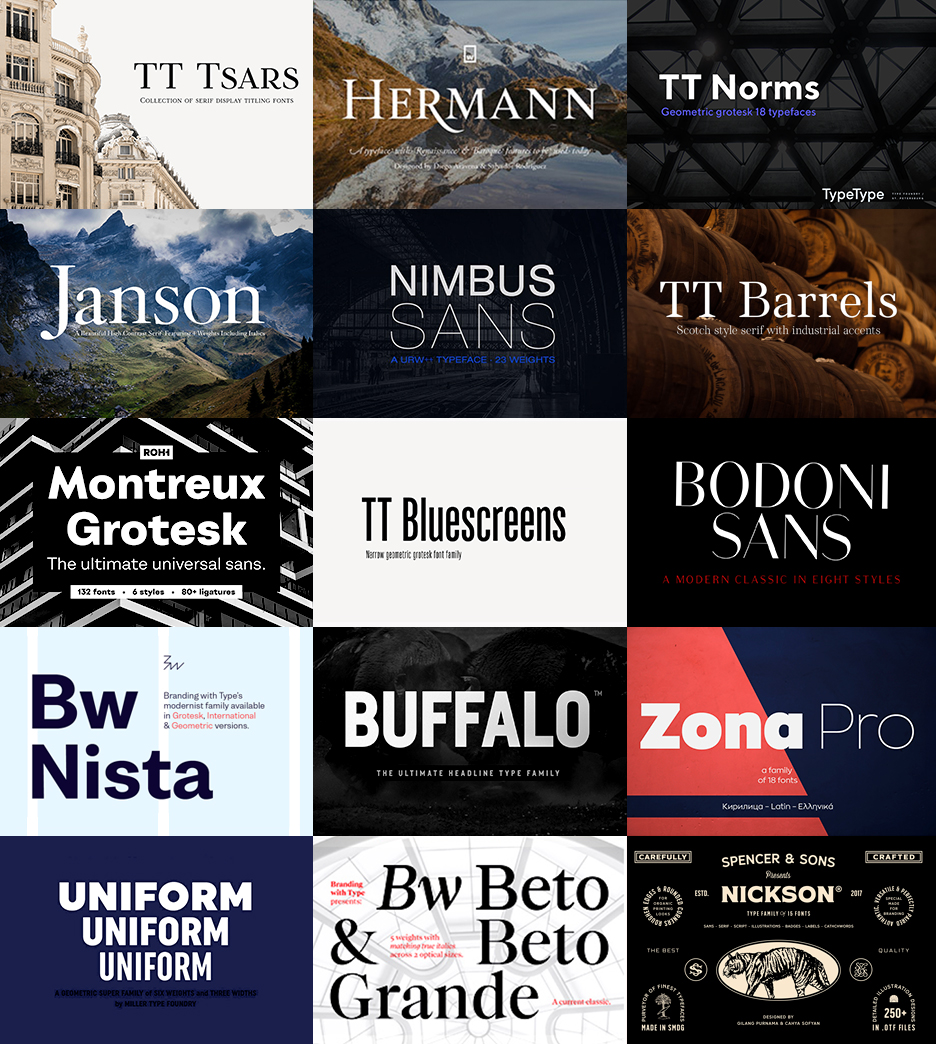
20書体を収録した美しいセリフフォント:TT TSARS
美しい20書体を揃えたセリフフォントコレクション「TT TSARS」。ユニークなリガチャ(合字)のデザインにも注目!ロゴデザインやブランディングに活躍するフォントです。
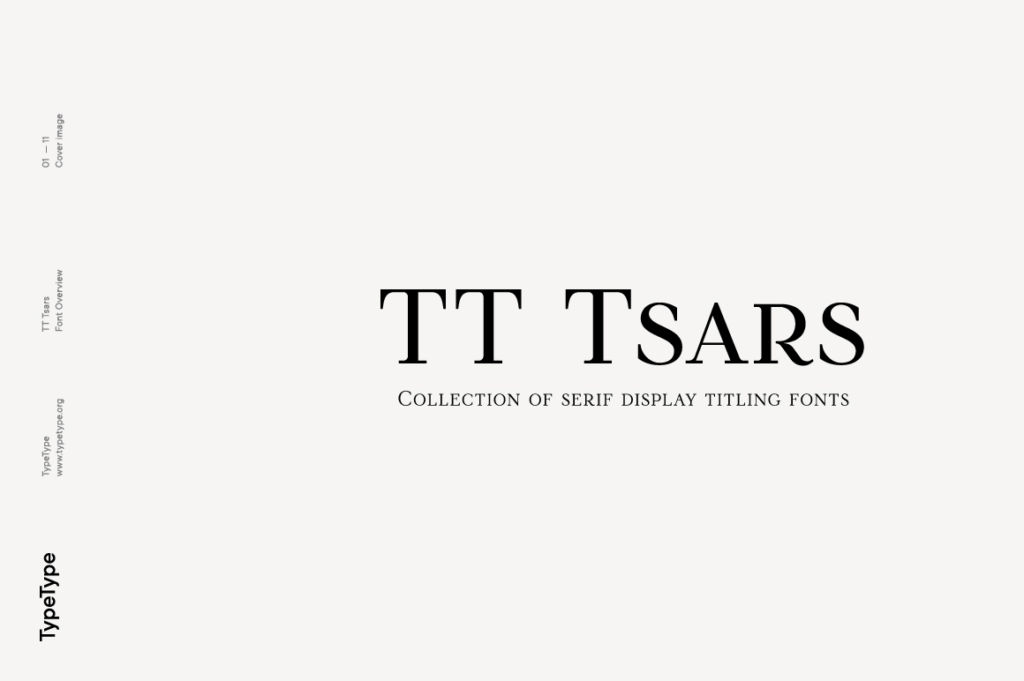
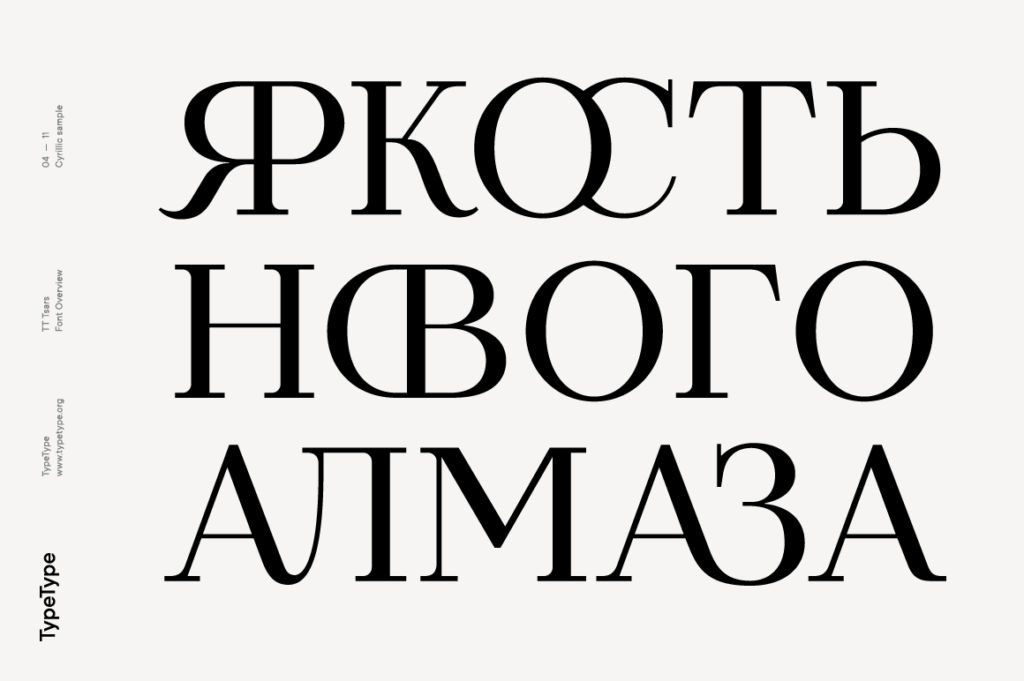
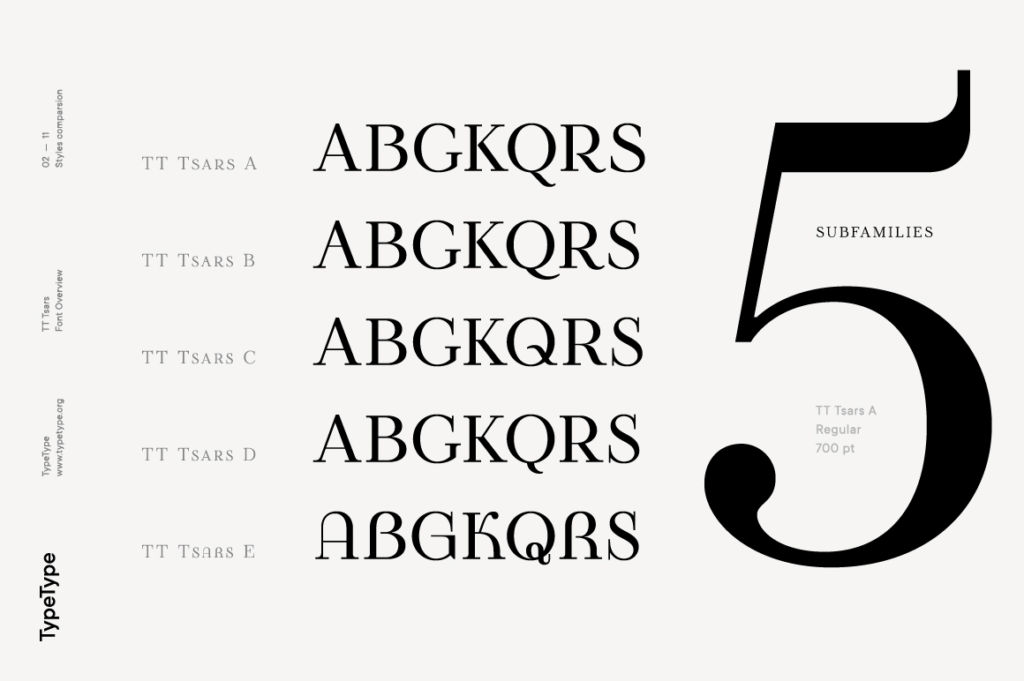
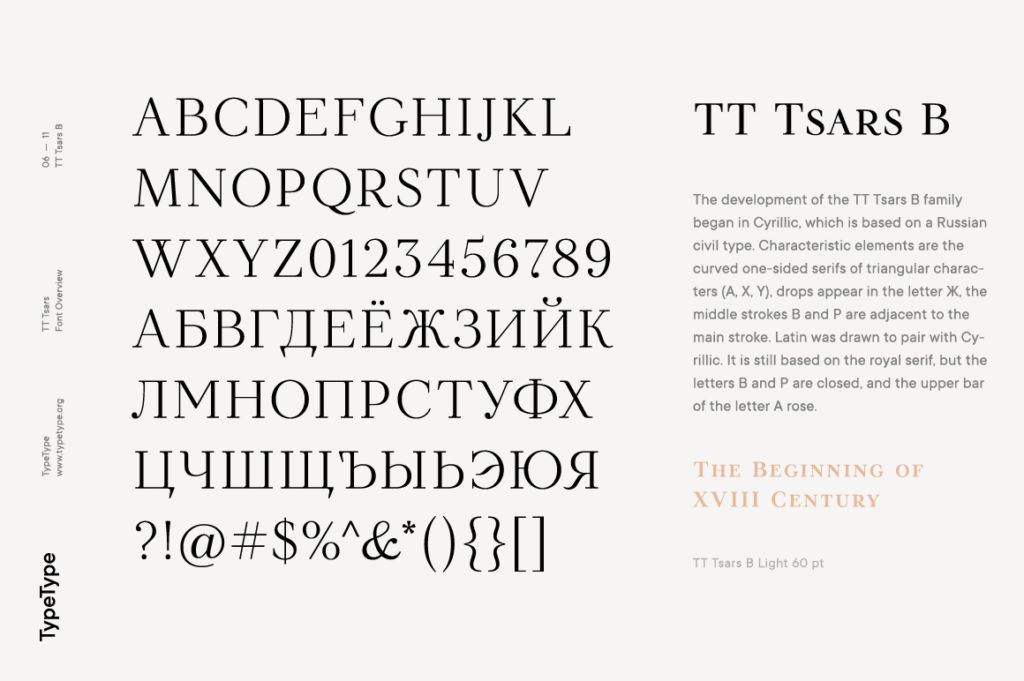
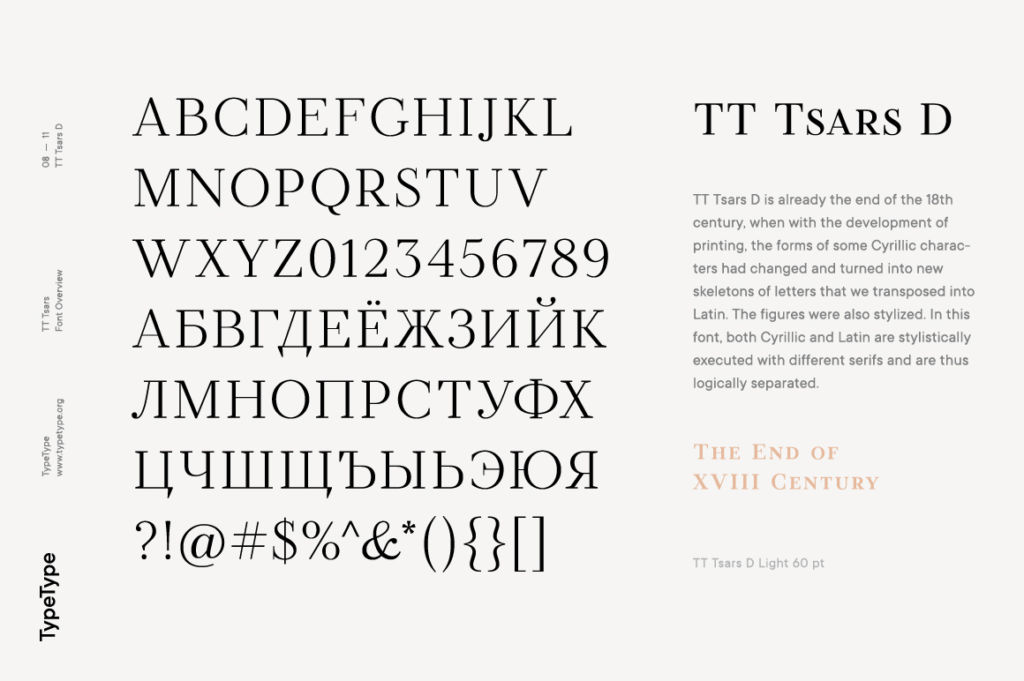
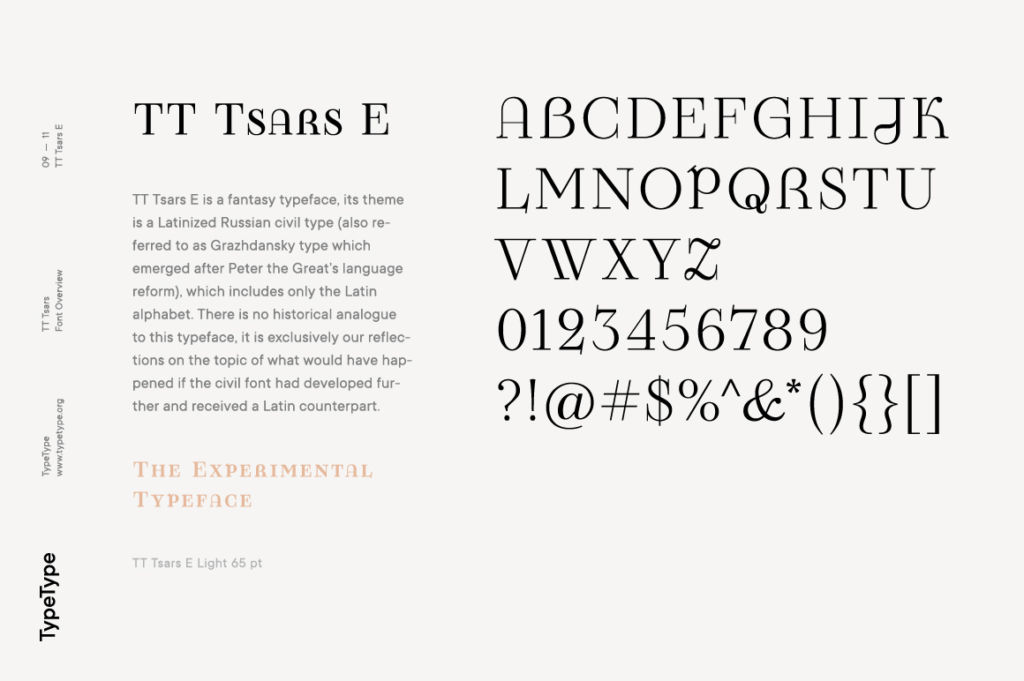
凝ったリガチャが楽しめるセリフフォント:TT BARRELS
18書体を収録したTypeTypeの「TT BARRELS」。ウェイトもライトからブラックまで用意されており、デザイン性の高いリガチャ(合字)も多数収録。一見かなり凝ったタイポグラフィも簡単にできますよ。
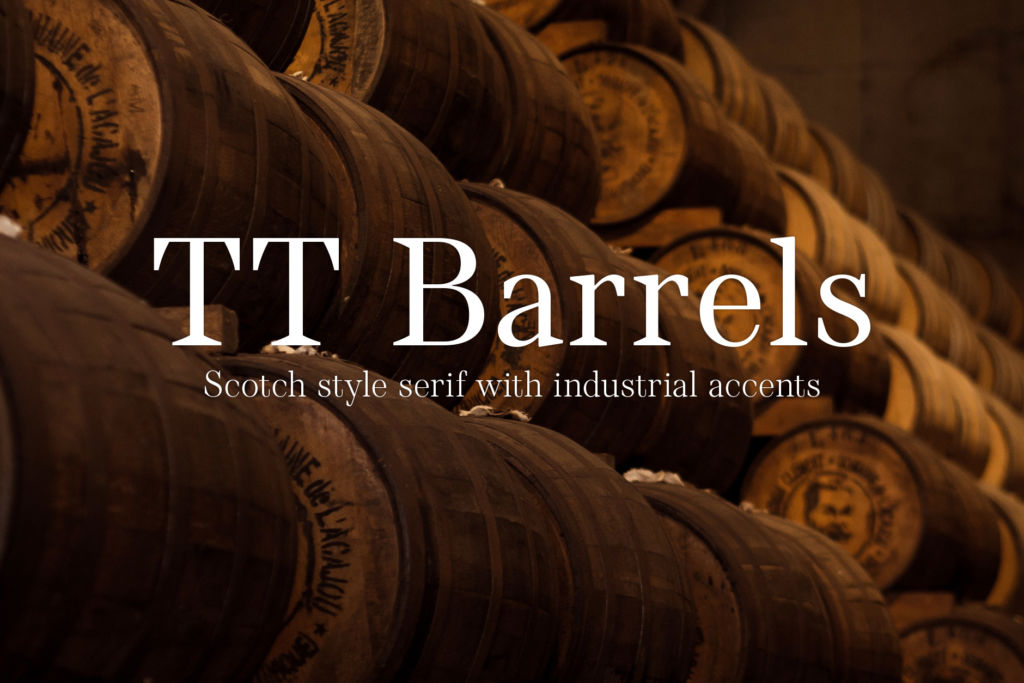
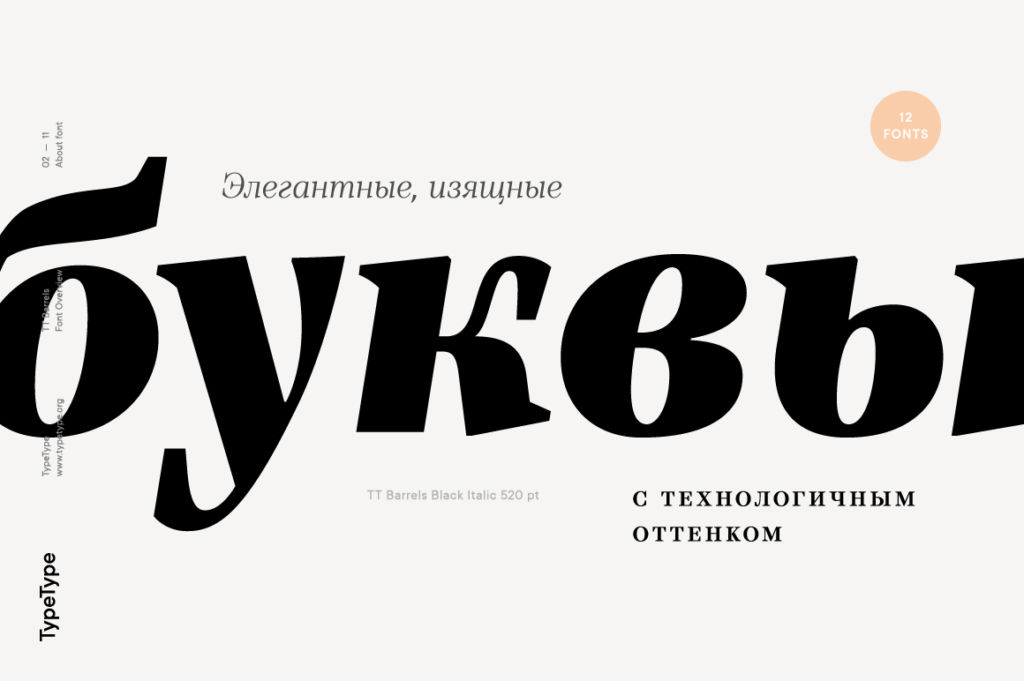
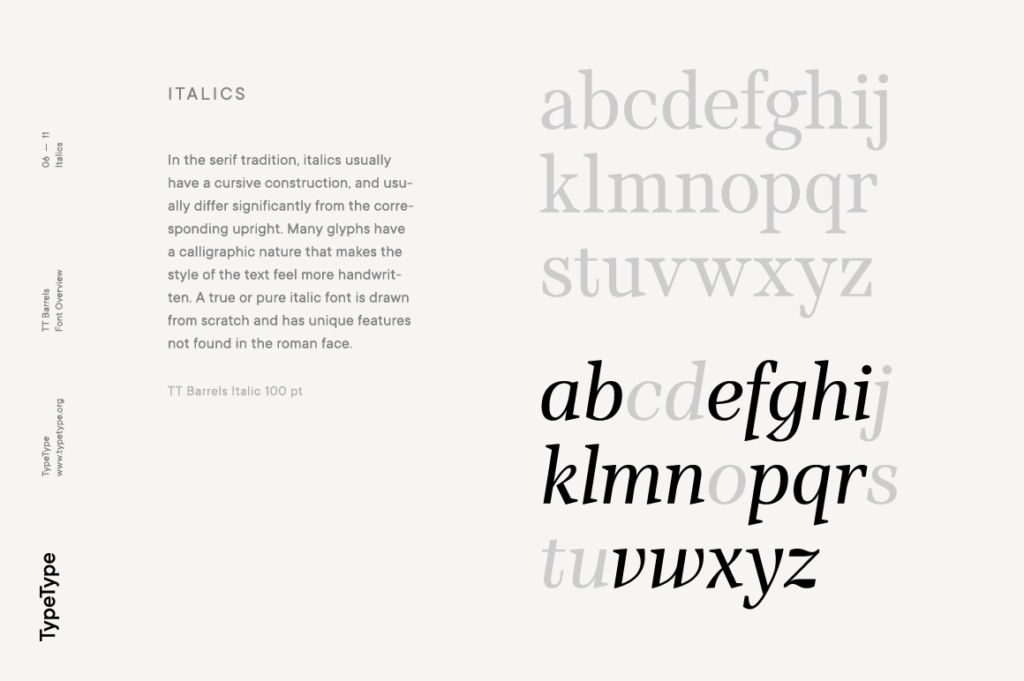
デザイン性の高い優雅なスウォッシュが魅力:HERMANN TYPEFACE
優雅なスウォッシュが魅力のセリフフォント「HERMANN TYPEFACE」。書籍の装丁やラベルのデザインをグッと格調高くしてくれます。
ウェイトのメリハリがポイント!BODONI SANS
縦ラインの太さが特徴の「BODONI SANS」。セリフフォントBODONIを連想させるクラシック感を残しつつ、現代風にアレンジされています。小さくても読みやすい文字で、様々な媒体に利用できますよ。
イラストやフレームを豊富に収録:S&S NICKSON FONT FAMILY
15種類のフォントはもちろん、イラストやフレームなど、ロゴやラベル作りに役立つデザイン素材もたっぷり収録した「S&S NICKSON FONT FAMILY」。便利なテンプレートつきなので、すぐにデザイン作業がはじめられます。